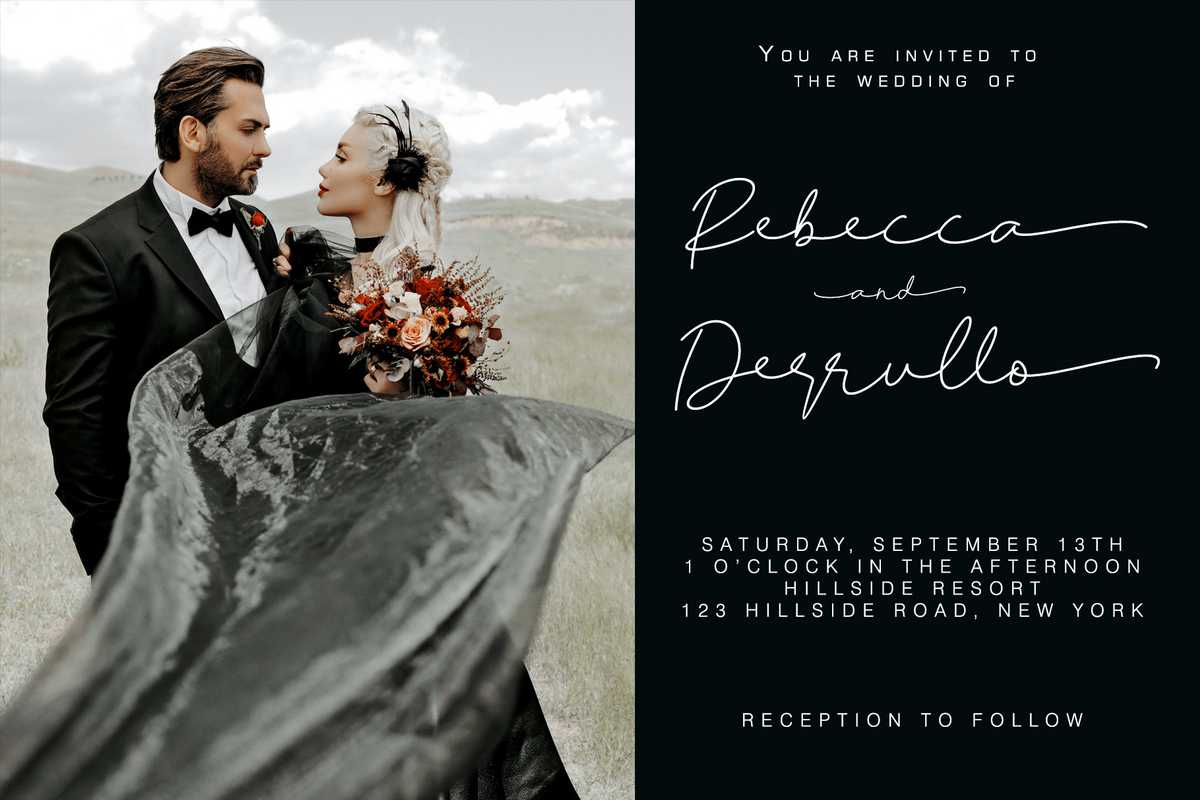
Bridge This A和WritenScript Font,带有Legant和Beautiful Look。Bridget A和WritenScript Font将具有完美的Legant Logo、Wedding Stationary、海报、quotes,短文本、品牌、web、图形设计和任何其他需要手写的项目